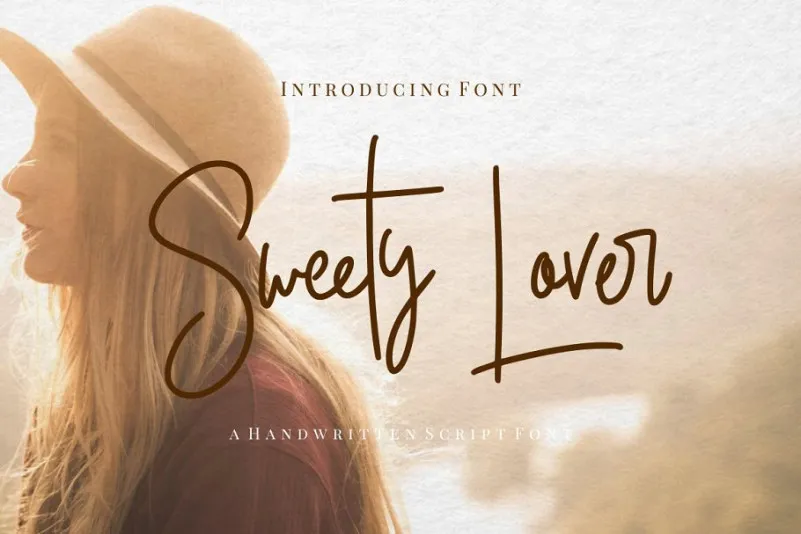
Sweety Lovers Signature Font – Download Grátis
A fonte Sweety Lovers Signature é uma font que traz a sofisticada e autêntica fluidez de uma escrita manuscrita contínua. Ela foi criada por Hamilton para atender tanto aos requisitos profissionais quanto aos dos elementos de marcação de um produto. Esta elegante e charmosa letra feita à mão é perfeita para a criação rápida e fácil de letras entrelaçadas, ideia que se destaca especialmente em assinaturas, cabeçalhos, capas, marcas de identidade, etiquetas, posters, logotipos, citações, embalagens de produtos, subtítulos, merchandising, mídias sociais e cartões de agradecimento. Com esta fonte, você pode facilmente expressar um toque personalizado em qualquer formato gráfico. O estilo autêntico e sofisticado da Sweety Lovers Signature torna-a uma opção indispensável para quem deseja dar à sua marca o seu próprio caráter único.